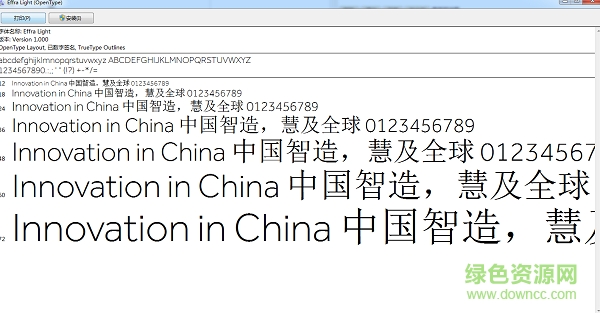
effra light是什么字體?effra-light字體是一款纖細(xì)的英文無(wú)襯線(xiàn)字體,線(xiàn)條筆直而流暢,字面干凈視覺(jué)效果很棒,本站還提供了很多和effra 相似的字體,歡迎免費(fèi)下載!
無(wú)襯線(xiàn)體擁有相同的曲率,筆直的線(xiàn)條,銳利的轉(zhuǎn)角,往往被用在標(biāo)題、較短的文字段落或者一些通俗讀物中,相比嚴(yán)肅正經(jīng)的襯線(xiàn)體,無(wú)襯線(xiàn)體給人一種休閑輕松的感覺(jué)。